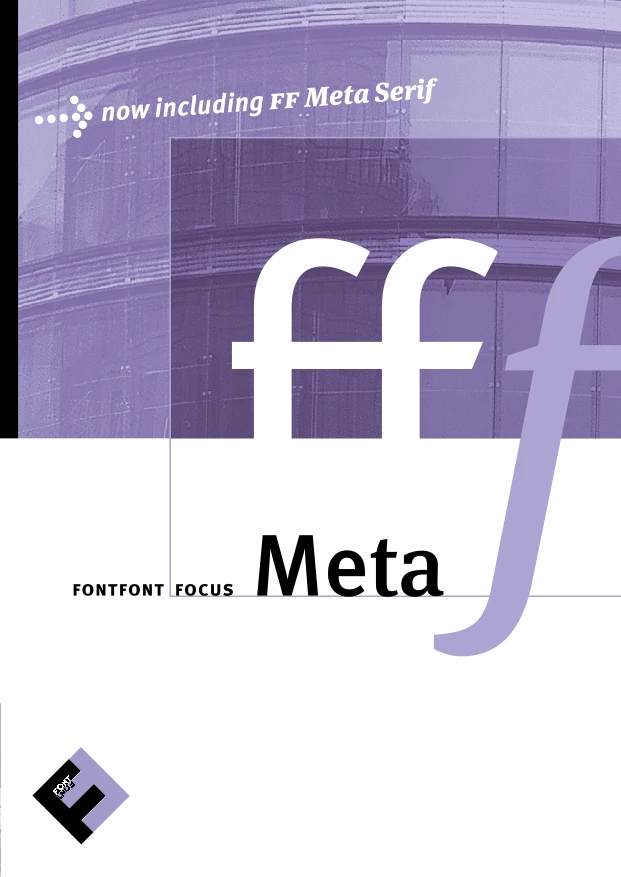
FF Meta es una familia tipográfica sanserif humanista diseñada por Erik Spiekermann y lanzada en 1991 a través de su biblioteca FontFont.
Según su autor, FF Meta pretendía ser una completa antítesis de la Helvetica, a la que consideraba “aburrida y sosa”. Surgió a partir de un encargo no implementado para el Oficina Federal de Correos de Alemania. A lo largo de la década de 1990, FF Meta fue acogida por la comunidad internacional del diseño con un amplio uso y difusión.
En 2007 se le agrega la versión serif.